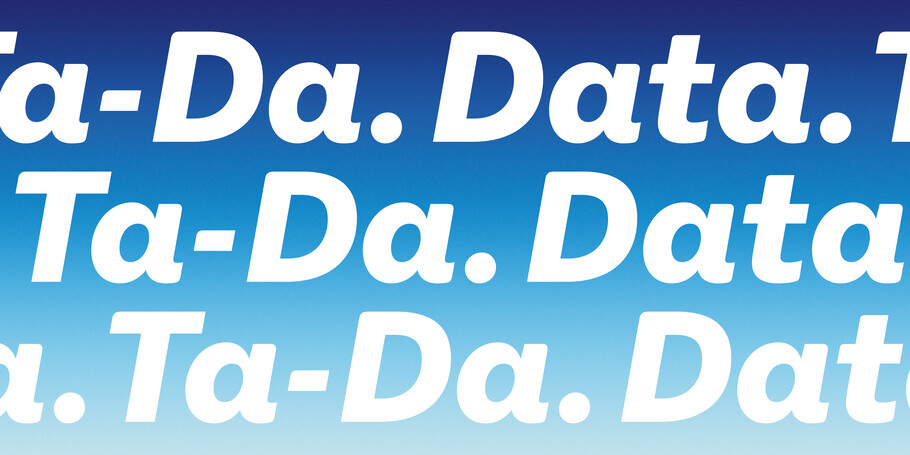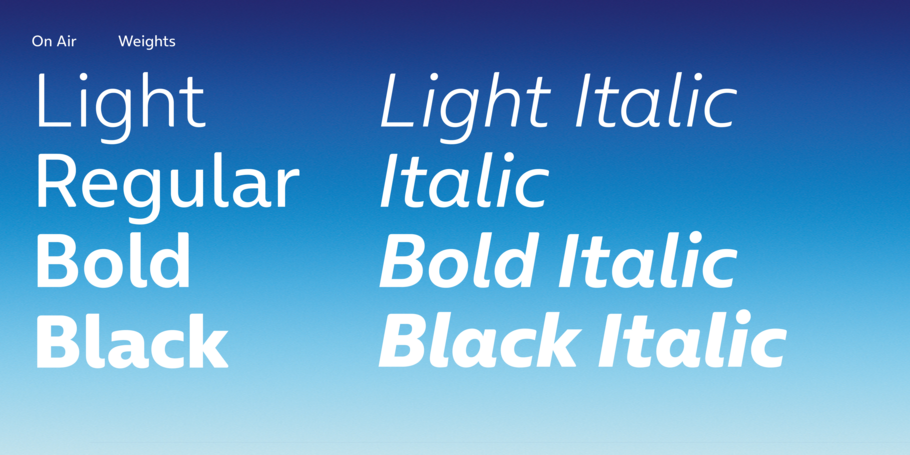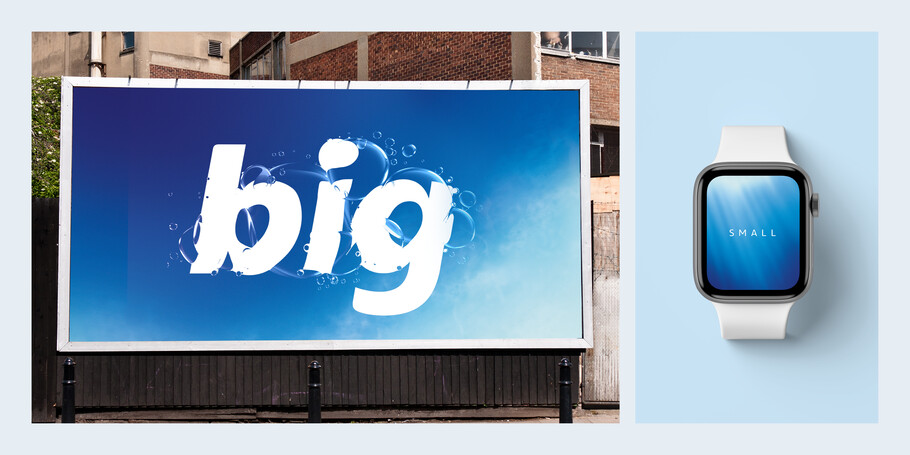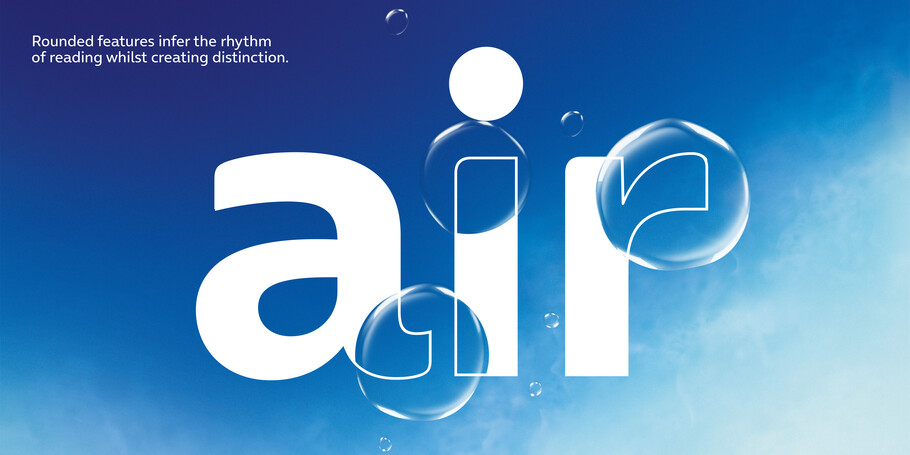
Warum die Pandemie Schriften freundlicher macht.
Unser Creative Type Director Phil Garnham sprach im Mai 2020 mit dem Economist über die Auswirkungen der Pandemie auf die Typografie. Angesichts des beispiellosen Jahres, das wir hinter uns hatten, gingen das britische Wirtschaftsmagazin und Phil der Frage nach, wie sich die Schriften in dieser Zeit entwickelt haben, um Lesern und Konsumenten zu erreichen.
Noch ist es zu früh, um genau vorherzusagen, wie stark die Pandemie Kunst und Design beeinflussen wird, aber die Werbetypografie hat sie bereits verändert. Erschütternde historische Ereignisse können das kreative Schaffen einer Generation durchaus in eine neue Richtung lenken. Der Ausbruch des indonesischen Vulkans Tambora im Jahr 1815 verursachte auf der ganzen Welt atmosphärische Störungen und 1816 ging als „das Jahr ohne Sommer“ in die Geschichte ein. Aus den Verwüstungen des Ersten Weltkriegs entstand die Moderne mit großen Innovationen in Literatur, Kunst … und auch der Typografie. Man denke nur an Futura und Gill Sans, beides frische, zukunftsweisende Schriften, die Mitte der 1920er Jahre geschaffen wurden und die Sehnsucht des Nachkriegsdesign nach etwas Neuem verkörperten.
Nicht nur typografisch geschulte Menschen wissen, dass beim Betrachten eines Schilds oder eines Logos mehr passiert als nur Lesen von Text. Wie Wörter gestaltet sind, kann genauso wichtig sein wie das, was sie aussagen. Schriften sind das visuelle Äquivalent zur Stimmfarbe. Sie würden die Einladung zu einer Party bestimmt nicht in Times New Roman oder eine ernst gemeinte Entschuldigung nicht in Comic Sans setzen. Für Unternehmen spielen Schriften eine wichtigere Rolle bei der Definition ihrer Identität als Farbe, Formen und Fotos.
Wenn sich die Welt verändert, ändert sich auch das, was wir sagen. So gesehen wirkt sich die Pandemie schon rein inhaltlich seit Monaten auf die geschriebene Kommunikation großer Marken aus. Dabei wurden häufig schlichte, geometrische und funktionale Schriften durch gerundete, weichere und ausdrucksstärkere ersetzt. Dieser Trend deutete sich schon vor der Pandemie an, eingeleitet von Marken mit selbstbewusst verspielten Identitäten wie Duolingo und Mailchimp. Nun hat er sich in der vergangenen Monaten beschleunigt. In Großbritannien haben Currys PC World, ein Elektrofachgeschäft, und Zoopla, eine Immobilien-Website, seelenlose Buchstaben durch charaktervolle Zeichen ersetzt. Um heute eine Waschmaschine zu verkaufen, brauchst du gewinnende Kurven und Bögen.
Der jüngste große Name, der diesen Weg beschritt, ist das Mobilfunkunternehmen O₂. Die Marke verabschiedete sich von Frutiger, eine weit verbreitete humanistische Sans, die seit 2002 im Einsatz war, um sie durch die Exklusivschrift On Air zu ersetzen, eine neue Schrift entwickelt in Zusammenarbeit mit dem Monotype Studio. Die abgerundeten Ecken und „die kalligrafischen Akzente von On Air geben der Familie eine menschliche Note“, sagt der Mitentwickler Phil Garnham. Das Ziel war, den Werbetexten von O₂ Wärme und Persönlichkeit zu verleihen. „Die Wirkung von maßgeschneiderten Schriften wie On Air funktioniert unterbewusst“, sagt Garnham, und niemand kann sich dieser emotionalen Tuchfühlung entziehen, was die Macht der Schrift in der visuellen Kommunikation unterstreicht. Trotzdem steckten große und kleine Marken seit der Jahrtausendwende in einer typografischen Sackgasse fest. Und wie so oft „war das Internet daran schuld“.
Zwei Jahrzehnte lang griffen internationale Marken zu generischen serifenlose Schriften, weil sie an Bildschirmen unterschiedlicher Größe und Auflösung am besten zu lesen waren. Nicht umsonst wird die ehemalige Hausschrift von O₂ häufig als „die lesbarste Schrift“ bezeichnet, weshalb sie noch heute in den meisten Leitsystemen von Flughäfen zu anzutreffen ist. Obwohl die Web-Technologie Entwicklern heute die Möglichkeit bietet, jede beliebige Schrift für eine Website zu verwenden, bevorzugen ihre Auftraggeber weiterhin kalte, geometrische Designs wie Avenir, Gotham oder Proxima Nova.
On Air
Schriften sind das visuelle Äquivalent zur Stimmfarbe.
Aber lesbar bedeutet nicht automatisch einprägsam … eher das Gegenteil. Im Jahr 2018 fanden Forscher des Royal Melbourne Institute of Technology heraus, dass Leser dazu neigen, den Inhalt von Texten, die aus allzu vertrauten Schriftarten gesetzt sind, zu überlesen und sich besser an die Botschaft erinnern, wenn das Lesen mit einer „angenehmen Schwierigkeit“ verknüpft ist.
Für die Tests entwarf man deshalb eine Schrift namens Sans Forgetica, bei der Teile von Buchstaben weggelassen wurden und das Gehirn diese Lücken ergänzen musste. Experimente mit Schülerinnen und Schülern zeigten, dass Texte, die in dieser Schrift gesetzt waren, mit größerer Zuverlässigkeit im Gedächtnis haften blieben als solche, die in Arial gesetzt waren. Später fanden andere Forscher keine belastbaren Beweise dafür, dass Sans Forgetica die Merkfähigkeit verbessere.
Unabhängig von ihrer Auswirkung auf unsere Achtsamkeit sind rein funktionale Schriften auf dem Rückzug. Das liegt zum einen daran, dass die Bildschirme bessere Auflösungen haben und Buchstabendetails sauber wiedergeben; andererseits hat das Font-Engineering heute die Qualität der digitalen Darstellung besser im Griff als vor 20 Jahren. In den vergangenen Monaten kam hinzu, dass die Pandemie die Art und Weise, wie Marken mit uns interagieren, verändert hat. Wenn Geschäfte geschlossen sind, wird die schriftliche Kommunikation über Websites, Apps oder E-Mail immer wichtiger. Schriften müssen heute härter arbeiten als je zuvor.
Lesbar bedeutet nicht unbedingt einprägsam – das Gegenteil kann der Fall sein.
Die jungen Schriften der Pandemie-Ära haben ein gemeinsames Thema: geschwungene Linien und abgerundete Formen. Aoife McGuinness, eine neurowissenschaftliche Beraterin bei der Marketingagentur HeyHuman, schreibt in ihrem Blog, dass unsere Gehirnzellen möglicherweise auf eine Art fest verdrahtet sind, die bestimmte Formen mit Konzepten oder Gefühlen assoziiert.
Eine Studie über Lebensmittelverpackungen aus dem Jahr 2017 ergab, dass Menschen runde Schriften mit süßem Geschmack und eckige mit saurem assoziieren. Gerade Linien und scharfe Winkel vermitteln Stabilität und Autorität, während Kurven und Kreise Weichheit, Milde und sogar Freundlichkeit transportieren. Freundliche Schriften können ein Mittel sein, den Verbrauchern näher zu kommen, insbesondere denjenigen, die sich angesichts der Einschränkungen einsam fühlen. Wenn Sie sich nicht mit ihren realen Freunden treffen können, warum sollten Sie sich nicht mit ihrem Breitbandanbieter oder hrem Klamottenshop anfreunden?
Wir hatten zuletzt viel Zeit zum Nachdenken. Den Verbrauchern sind Nachhaltigkeit und Auswahl heute wichtiger als 2019, und die Unternehmen müssen darauf hören. Wenn kalte, geometrische Buchstaben eine gewisse Autorität, ja sogar Arroganz ausdrücken, dann spiegelt der Wechsel zu wärmeren, abgerundeten Buchstabenformen einen maßvollen, zurückhaltenden Ansatz wider. Für Marken ist die Anpassung ihres Schriftbildes eine einfach und schnelle Möglichkeit zu zeigen, dass sie mit der Zeit gehen oder ihr sogar voraus sind.